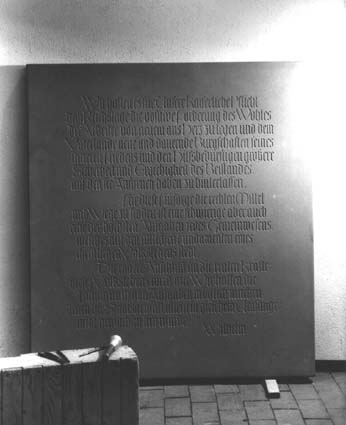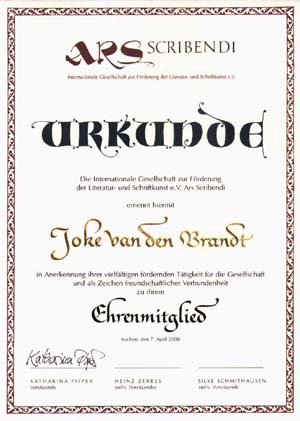
Zeitschrift Ars Scribendi 1/2000
die erste in diesem Jahrtausend!
| Alle reden vom Internet, Computer, virtuellen Welten oder http://www. Sollen wir Kalligrafen uns davon ausschließen? Nein, denn die interglobale Kommunikation bietet wirklich phantastische Möglichkeiten des Austausches unter den Schreibbesessenen, und man braucht dabei ja nicht gleich die Feder aus der Hand zu legen! Roland Nyffeler, der Präsident der Schweizerischen Kalligrafischen Gesellschaft, schreibt in seinem Vorwort des Mitteilungsblattes Nr.17 folgendes: "Jedesmal, wenn ich meinen Einstieg ins www: World-Wide-Web mit der schon fast heiligen Mantra 'http://' beginne, überlege ich mir, wie wohl ein 'http: hyper-text-transfer-protocol' bei den Benediktiner Buchmalern des frühen Mittelalters ausgesehen haben mag...". | Der Zeitgeist schwingt am Anfang des dritten Jahrtausends auf der technischen Welle, und nun geht alle Welt ins Internet. Auch wir von Ars Scribendi sind "drin" .Zwar liegt noch ein ganzes Stück Arbeit vor uns, was die Vollständigkeitder Seiten angeht, doch gelangt man seit inzwischen einiger Zeit auf diese Seiten im Netz, zunächst über die Website von Katharina Pieper. Es kamen bereits interessante Kontakte, zum Beispiel auch zu unseren Kursdozenten zustande. Hoffen wir, daß weiterhin aus Virtualität auch ab und zu Realität wird! | |||
Johannes Gutenberg, der "Mann des Jahrtausends"
In unserer 28 Seiten starken Zeitschrift steht der "Mann des Jahrtausends", der "man of the millennium" an erster Stelle: Johannes Gutenberg, analysiert und charakterisiert von Dr. Christian Klinger. Fachlich kompetent und zugleich spannend und amüsant hat Dr. Klinger das Leben und Werk des Mainzer Druckers zusammengetragen: ein Bericht der Spitzenklasse, den es sich zu lesen lohnt!
.......................................Kapitalis von Prof. Werner Schneider: Jahresgabe 1999
Neuigkeiten:
| Prof. Werner Schneider wurde 65 Jahre
alt: ein fanatischer Schriftkünstler und Type-Designer auf dem Höhepunkt
seiner Schaffenskraft.
* Joke van den Brandt, Präsidentin der flämischen Vereinigung "Kalligrafia", ist von Ars Scribendi zum Ehrenmitglied ernannt worden. * "Literarisches": Der Dichter Henning Sabo aus Mainz bringt Kurzgeschichten und Gedichte in seinem neuen Buch InneHalt heraus. * |
100 Jahre Gutenberg-Gesellschaft: ein Jahrbuch, herausgegeben
vom Hermann-Schmidt-Verlag in Mainz.
Arbeiten von Prof. Werner Eikel:
Ein Großteil der Werke des Gründes der Gesellschaft Ars Scribendi, Prof. Werner Eikel aus Aachen (verstorben 1998) befindet sich inzwischen bei unserem Kuratoriumsmitglied Frau Gerhild Vollmer in Dortmund. Viele wunderbare Arbeiten und Texte, auf die unterschiedlichsten Arten gestaltet sind: von lateinischen Lettern über hebräische bis hin zu arabischen - für Werner Eikel schien es keine Grenzen zu geben. Eine Vielfalt, die uns immer wieder die grenzenlose Kreativität und Schaffenskraft unseres Gründers vor Augen führt und voller Respekt den Hut ziehen läßt.
Kursberichte:
z.B. über den englischen Kalligrafen Peter Thornton in der ag-Galerie in Wentorf bei Hamburg (Antje und Günter Stapelfeld), eine Vorankündigung des Steinbildhauer-Seminars bei Karl-Josef Schneider und Markus Weisheit in Siegburg (obiger Stein ist eine wunderbare Textur, gehauen in Stein von Karl Josef Schneider), ein Seminar in Chemnitz mit dem bekannten Kalligrafen Heinz Schumann oder einen Erfahrungsbericht über das Seminar "Humanistische Kursive" bei Rolf Frank Römhild in Olpe beleuchten die vielfältigen Angebote an interessanten Kursen, die von unserer Gesellschaft organisiert werden.
Ein Philosoph als Anarchist des Alphabets:
Dr. G.L.J. Schönbeck ist Wissenschaftler und Buchkünstler zugleich
| Erstmals in der Geschichte der Typografie ist es geschehen, dass ein Wissenschaftler die typografische Notwendigkeit für seine Studien erkennt und aus ästhetischen Gründen selbst seine ganz eigene Schrift für seine Dissertation entwirft. Gottfried Lodewijk Johann Schönbeck aus Amsterdam schreibt 10 Jahre an seiner Doktorarbeit, die die Notationen des Heraklit zur Sonne zum Thema hat. Allein der wissenschaftliche Horizont übersteigt bei weitem den Rahmen des bisher Gewesenen, und nun entwirft der fanatische Perfektionist auch noch über 2000 Zeichen, Zahlen, Ligaturen, Ziffern, Sonderzeichen | und eine ganz eigene griechische Schrift für sein uvre Sunbowl or Symbol, weil die bestehenden Typen die archaischen Texte nicht akkurat genug wiedergeben können. Ohne die moderne Computertechnik wäre diese Entwicklung nie möglich gewesen. Für sein Werk ist der Wissenschaftler nicht nur mit einem Preis der Stiftung Buchkunst der Frankfurter Buchmesse 1999 ausgezeichnet worden, sondern auch mit dem Max Reneman Preis der Niederlande für die buchkünstlerische Arbeit. Es ist ein Gesamtkunstwerk entstanden, das weltweit seinesgleichen sucht. |